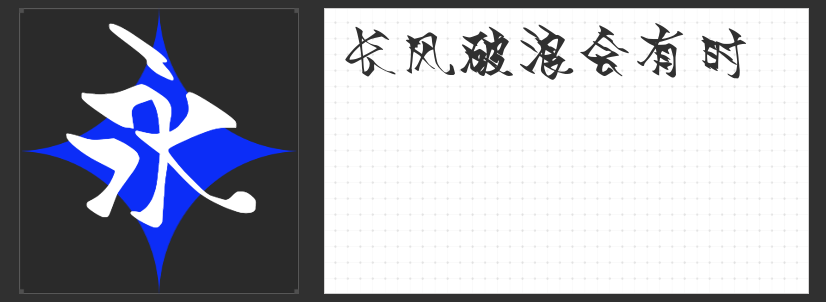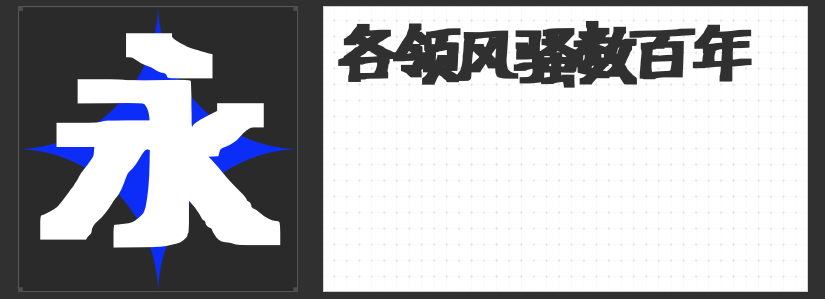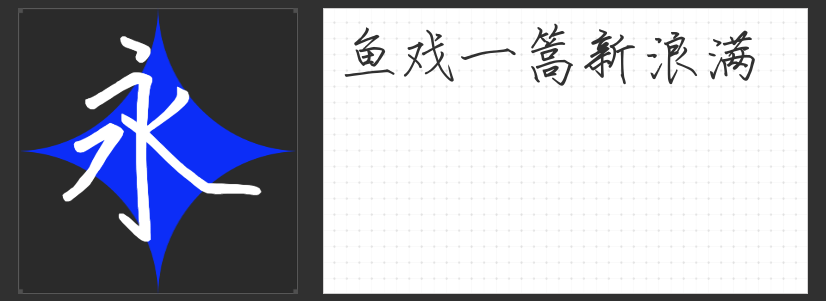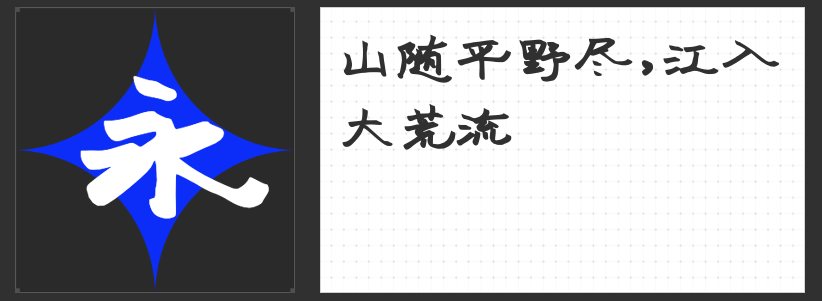
四款手写风格字库推荐:以笔触唤醒设计灵魂
在数字化浪潮中,手写字体的温度与人文气息愈发珍贵。本文精选四款由书法家安景臣设计的特色字库,它们以传统为根基,融入现代审美与创作巧思,为设计师提供兼具艺术性与实用性的表达工具。
一、安景臣海市体
这款字体突破常规手写框架,以“变化多端”为核心设计语言。笔触时而如流云舒展,时而似骤雨倾泻,在虚实相生间构建出梦幻般的视觉韵律。设计师通过特殊笔具与创意构思的融合,赋予字体强烈的动态感与辨识度,尤其适合追求艺术突破的品牌宣传,既能瞬间抓住青年群体的视线,又能为文化场景注入先锋气质。
二、安景臣新隶书体
在传统隶书的“蚕头燕尾”基础上,新隶书体融入硬朗的现代线条与个性化笔锋。它既保留了隶书的古朴厚重,又通过结构调整与笔画简化提升实用性,形成独特的“新古典主义”风格。这款字体适用于需要文化底蕴的场景,如仿古出版、影视字幕等,既能传递历史厚重感,又能以鲜明个性强化品牌记忆。
三、安景臣新瘦金体
源于宋徽宗瘦金体的基因,经硬笔书写工具重构后,这款字体在保留“铁画银钩”精髓的同时,更适配现代显示媒介。加粗修正后的笔画兼具书法的飘逸与印刷体的清晰,无论是手机屏幕的精细呈现,还是商标标志的视觉冲击,都能游刃有余地平衡艺术性与功能性。
四、安景臣美术体
作为书法体与标准美术体的过渡形态,这款字体以粗犷豪放的笔触打破常规审美框架。通过刻意强化的笔画对比与张力结构,营造出极具视觉冲击力的宣传效果,尤其适合需要“过目不忘”特质的广告场景。其设计哲学在于:用书法的不羁灵魂,唤醒印刷体的生命力。
这四款字库以手写为起点,却延伸出无限设计可能。它们不仅是文字载体,更是情感与文化的视觉翻译官,等待设计师以创意激活其独特魅力。